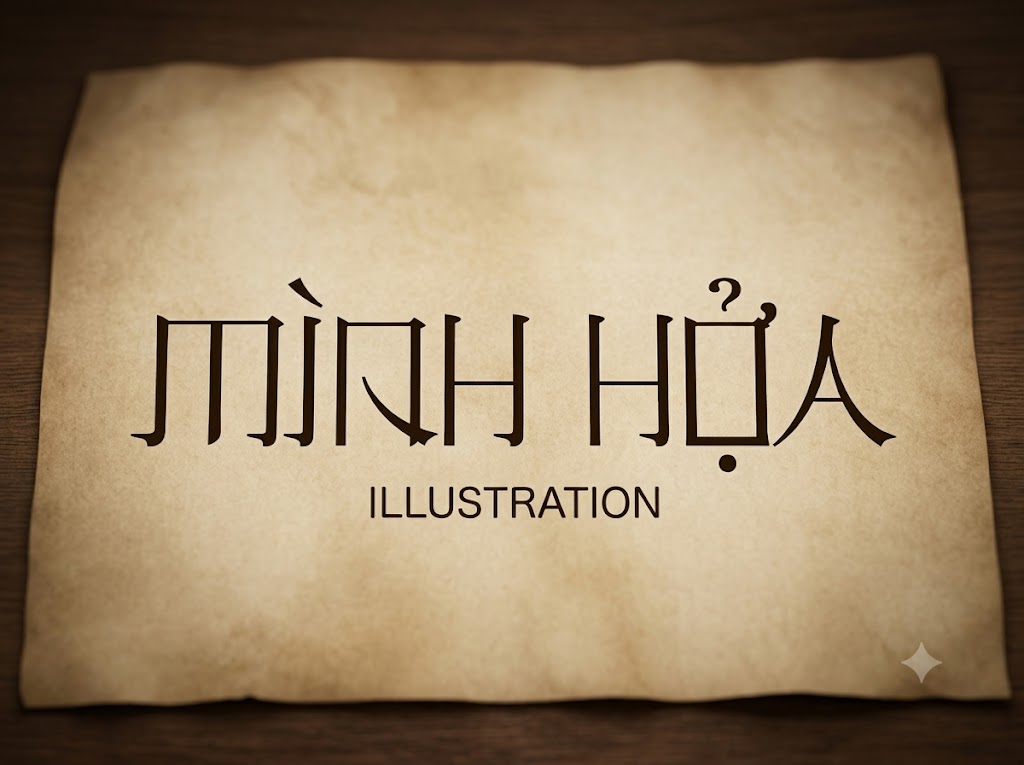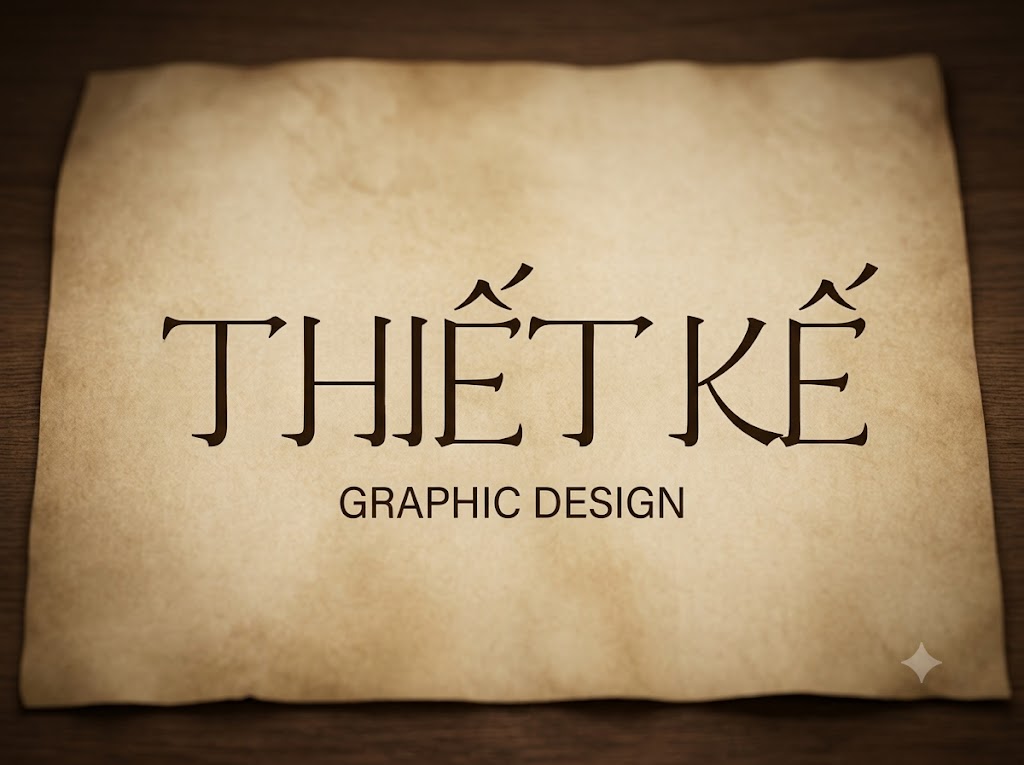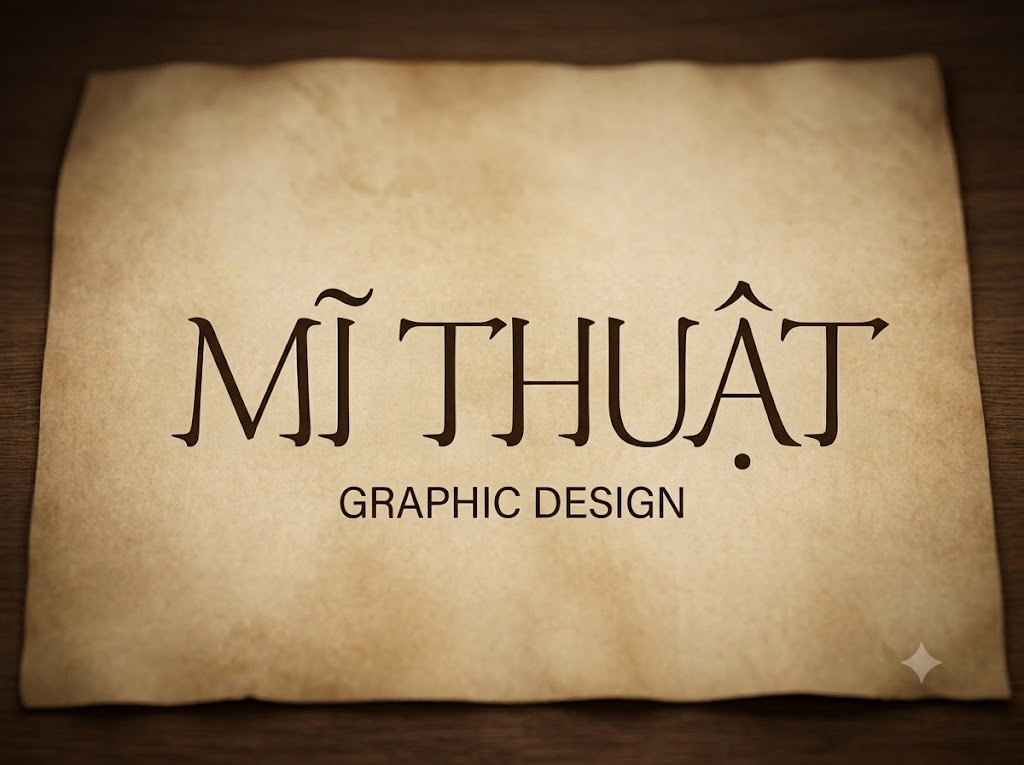
1FTV Romaji Mincho
Trong thị trường thiết kế đồ họa và sáng tạo nội dung số, bên cạnh các phông chữ hiện đại tối giản của phương Tây, xu hướng sử dụng các kiểu chữ mang hơi hướng văn hóa bản địa, phong cách Á Đông (Oriental/Asian Style) đang ngày càng lên ngôi. Những bộ phông chữ này sở hữu một sức hút thị giác đặc biệt, giúp ấn phẩm tự động kể một câu chuyện đầy tính chiều sâu, kết nối mạnh mẽ giữa nét truyền thống cổ điển và hơi thở đương đại.
Nếu bạn đang tìm kiếm một bộ chữ hiển thị độc lạ, mang đậm dấu ấn nghệ thuật cọ lông để làm tiêu đề phim, thiết kế bao bì e-commerce hay làm nổi bật nội dung trên các nền tảng video ngắn, thì font 1FTV Romaji Mincho chính là giải pháp không thể bỏ qua.
Giới thiệu về font 1FTV Romaji Mincho
Font 1FTV Romaji Mincho là một bộ chữ hiển thị (display font) độc đáo được thiết kế nhằm mô phỏng lại cấu trúc đường nét của nghệ thuật viết chữ Kanji và Katakana Nhật Bản trên hệ ký tự Latin (Romaji).
Bộ phông chữ này được ra mắt ở phiên bản Version 1.00 2013, mang lại một cấu trúc hình khối vô cùng vững chãi và độ nhận diện văn hóa cực kỳ cao.
Đặc điểm nổi bật của phong cách thiết kế Romaji Mincho
Sức hút lớn nhất của font 1FTV Romaji Mincho đến từ cách tạo hình giả cổ phong (Faux-Asian) với những đường nét mô phỏng lại nhịp điệu nhấn nhả lực của bút lông:
Nét cọ sắc sảo mang dáng dấp Mincho: Các ký tự được chấm phá bằng những đường vát nhọn ở đầu nét, đường gạch ngang thanh mảnh mảnh mai kết hợp với các nét đứng dày dặn, gợi liên tưởng trực tiếp đến phong cách khắc chữ gỗ và thư pháp truyền thống Nhật Bản.
Cấu trúc All-Caps đồng bộ: Phông chữ được xây dựng theo định dạng viết hoa đồng bộ cho cả hai hàng ký tự trên hệ thống. Lựa chọn thiết kế này tạo ra một cao độ đồng đều tuyệt đối, giúp các tầng tiêu đề trở nên vuông vắn, kiên cố và tạo tác động thị giác mạnh mẽ.
Biến điệu hình học độc lạ: Các ký tự như A, K, X, O được cách điệu một cách táo bạo bằng những nét xiên thẳng dứt khoát, mang lại cảm giác vừa cổ kính lại vừa có nét phá cách của tinh thần đồ họa hiện đại.
Hệ thống khoảng cách chữ (kerning) và độ giãn dòng đã được căn chỉnh khoa học, giúp các ký tự mang phom dáng hình khối đặc trưng này khi đứng cạnh nhau không bị dính nét hay gây cảm giác rối mắt cho người xem.
Tích hợp trọn vẹn bộ chữ cái viết hoa đồng bộ, dãy chữ số từ 0-9 cùng hệ thống ký tự đặc biệt, dấu câu thông dụng (
Bản Việt hóa chuẩn chỉnh giúp các nhà sáng tạo nội dung hoàn toàn yên tâm thiết kế các văn bản tiếng Việt có dấu mà không lo gặp phải tình trạng nhảy font hay thiếu ký tự khi gõ.
Hình ảnh demo thực tế của font 1FTV Romaji Mincho
Kích thước nhỏ (12pt – 24pt): Dù sở hữu cấu trúc chữ biến điệu phức tạp, hệ thống nét chữ và dãy chữ số vẫn hiển thị ngay ngắn, rõ ràng, đảm bảo tính dễ đọc trên giao diện màn hình di động.
Kích thước lớn (36pt – 72pt): Đây là không gian lý tưởng nhất để font chữ phô diễn toàn bộ cái hồn nghệ thuật thư pháp, tạo tác động thị giác mạnh mẽ chiếm trọn sự chú ý cho các dòng headline chính.
Ứng dụng của font Romaji Mincho trong thiết kế đồ họa và làm video
Sở hữu nét cá tính đậm đà bản sắc, vững chãi và cấu trúc hình khối độc bản, font 1FTV Romaji Mincho mở ra không gian ứng dụng vô cùng rộng lớn cho các dự án truyền thông và marketing:
Làm tiêu đề video ngắn (TikTok, Reels, Shorts): Phông chữ này là lựa chọn tuyệt vời cho các video thuộc chủ đề review ẩm thực (món Nhật, món Hàn, đồ nướng, lẩu, e-commerce food), vlog du lịch, trải nghiệm văn hóa hoặc video cinematic cổ phong. Kiểu dáng chữ đứng giúp các câu giật tít hiển thị vô cùng nổi bật và gọn gàng trên khung hình dọc tỷ lệ 9:16 của thiết bị di động.
Thiết kế ảnh thu nhỏ YouTube (Thumbnail): Vũ khí hạng nặng để tăng tỷ lệ nhấp chuột (CTR) cho các kênh làm nội dung anime, manga, review phim ảnh, văn hóa lịch sử, hoặc các video âm nhạc lofi, chill-hop hướng tới giới trẻ nhờ độ nhận diện thị giác cực cao từ khoảng cách xa.
Nhận diện thương hiệu và bao bì ngành F&B: Hoàn hảo để thiết kế logo dạng chữ khối, menu nhà hàng, bảng hiệu quảng cáo, poster sự kiện hoặc nhãn mác bao bì sản phẩm cho các tiệm trà sữa, quán cà phê phong cách tối giản Nhật Bản, local brand quần áo hoặc các studio sáng tạo yêu thích phong cách fusion.